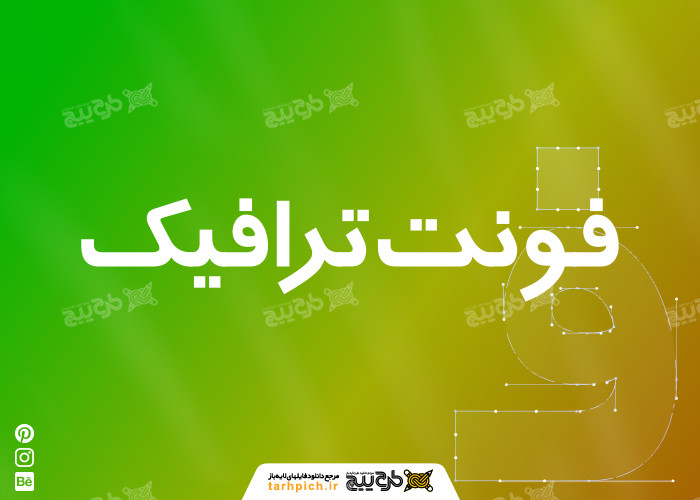
فونت ترافیک
فونت فارسی ترافیک یک فونت مناسب برای طراحی گرافیک است. از این فونت عموما در طراحی طرح‌های کارت ویزیت استفاده می‌شود. همچنین فونت ترافیک به دلیل خوانایی بالایی که دارد، برای نگارش کتاب یا طراحی طرح جلد کتاب بسیار مناسب است. به همین دلیل در موکاپ‌های کتاب از این فونت بسیار استفاده شده است.فونت  traffic در دو نسخه بولد و نرمال طراحی شده است. برای دانلود فونت‌های رایگان فارسی کافی است روی لینک کلیک کنید.سایت لایه باز طرح پیچ برای دانلود و مشاهده انواع فونت‌های فارسی در خدمت شماست.
طراح فونت ترافیک
فونت ترافیک را شرکت برنا رایانه طراحی کرده است و به صورت رایگان در اختیار عموم ایرانیان قرار داده است. از دیگر فونت‌های طراحی شده توسط شرکت برنا رایانه  می‌توان به فونت‌های بی یکان، فونت آریا، فونت آرش، فونت بدر، فونت یاقوت  و... اشاره کرد.